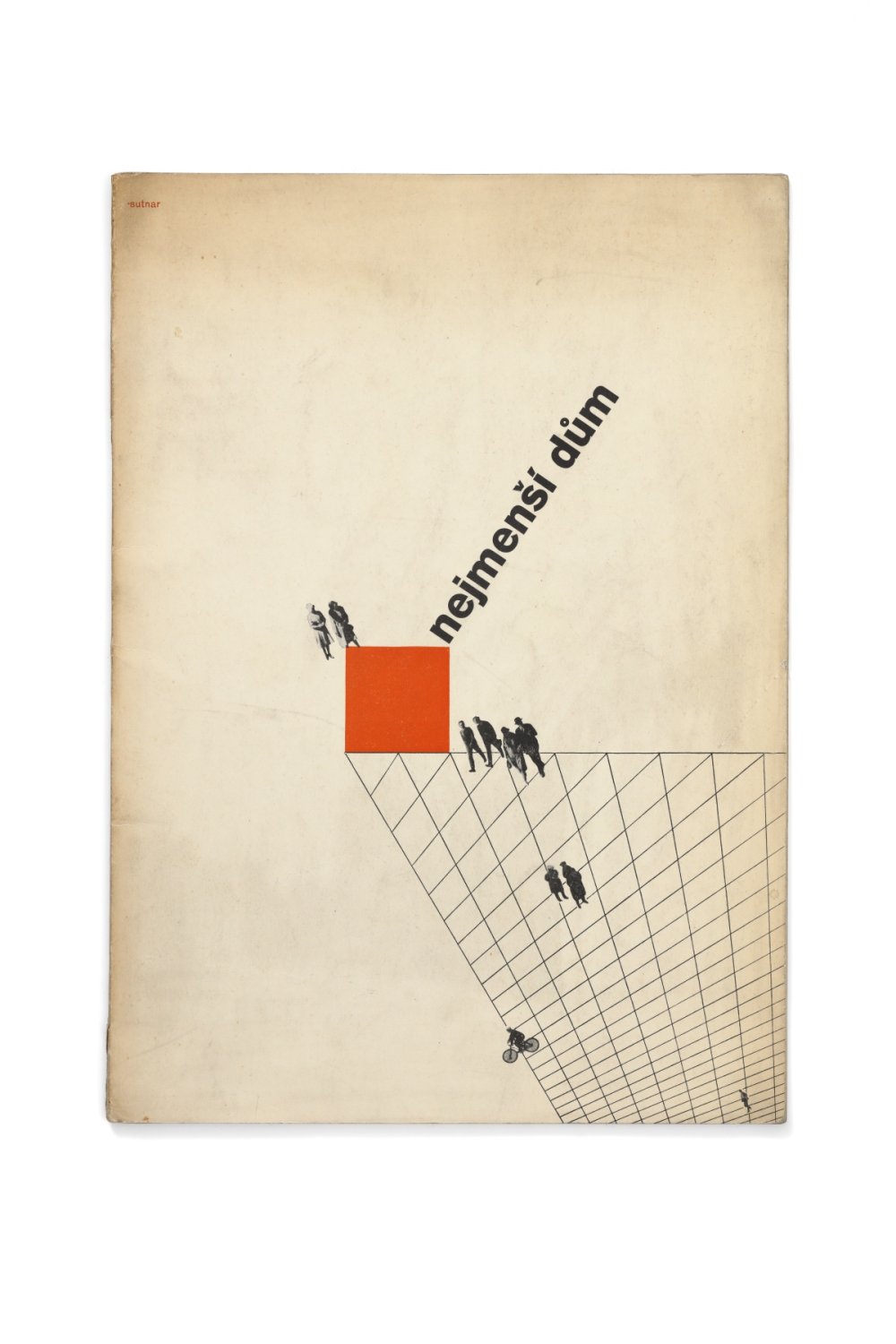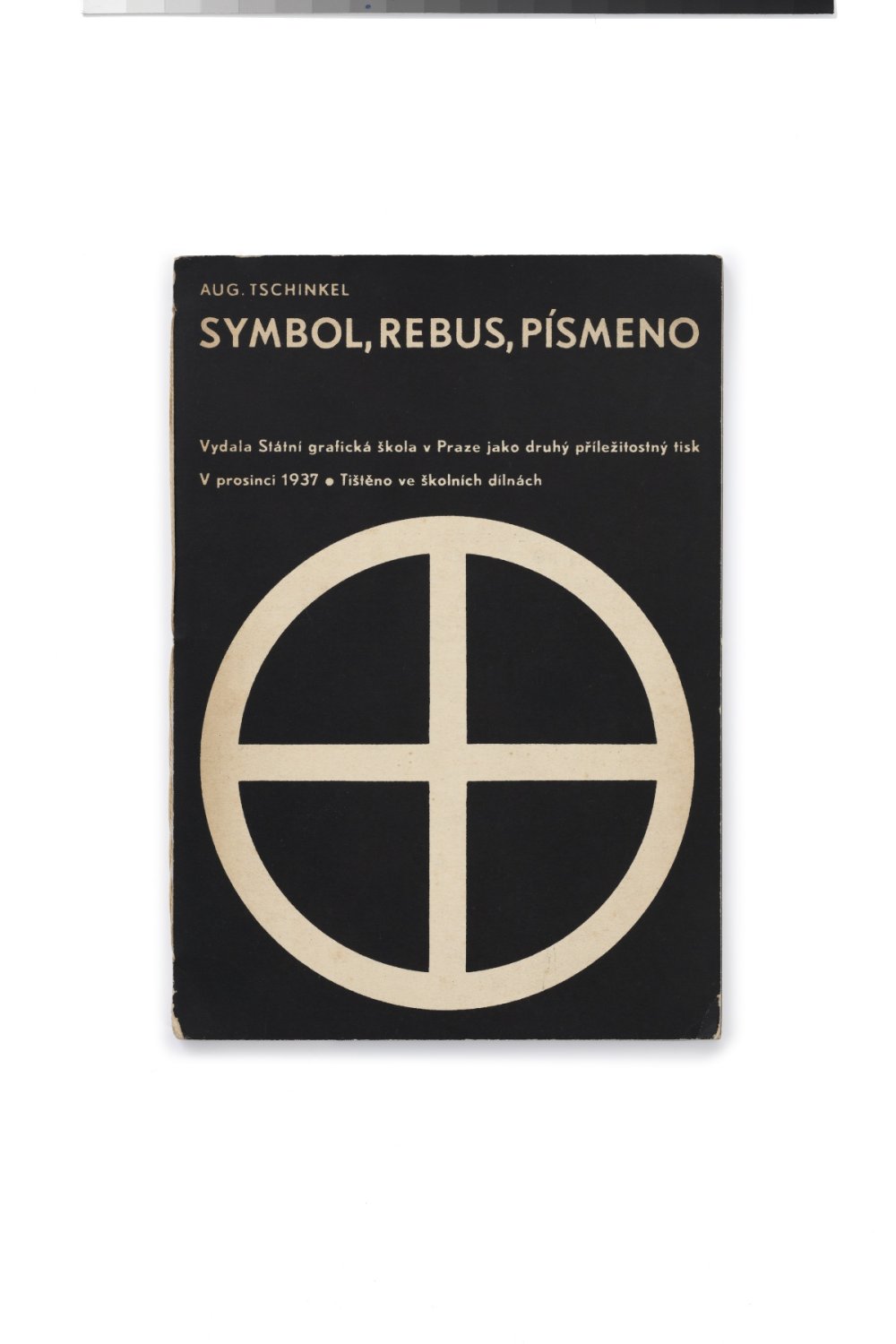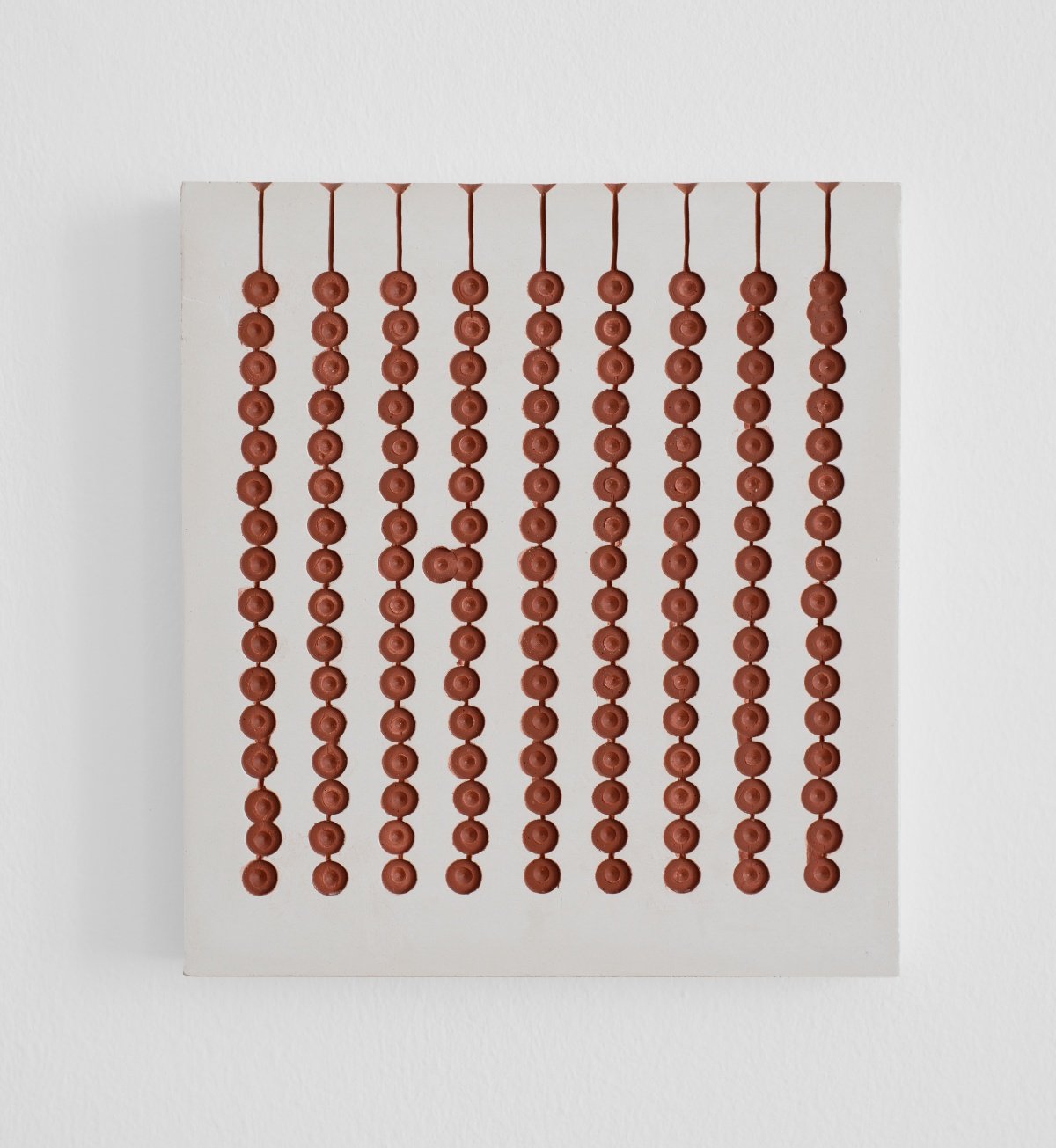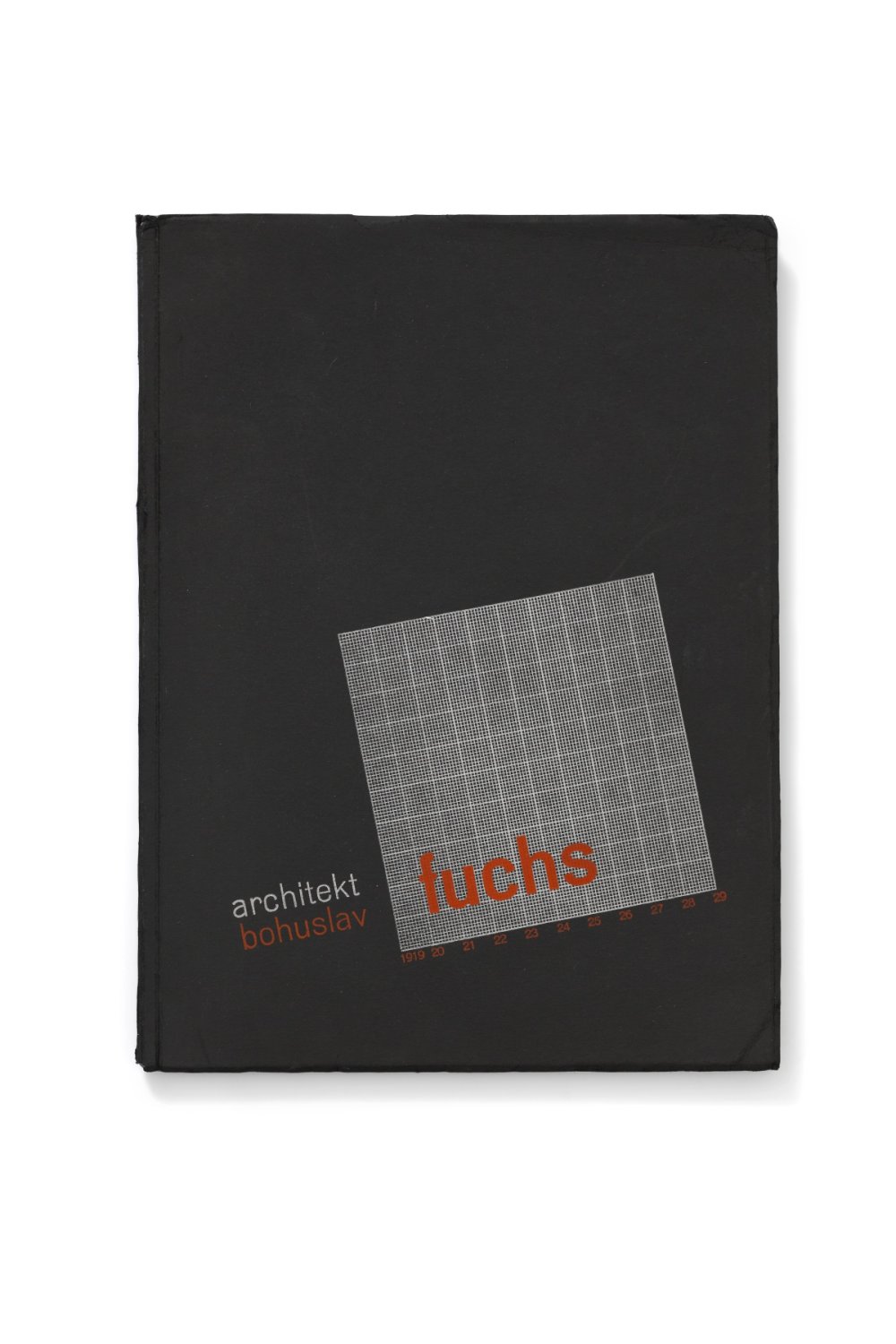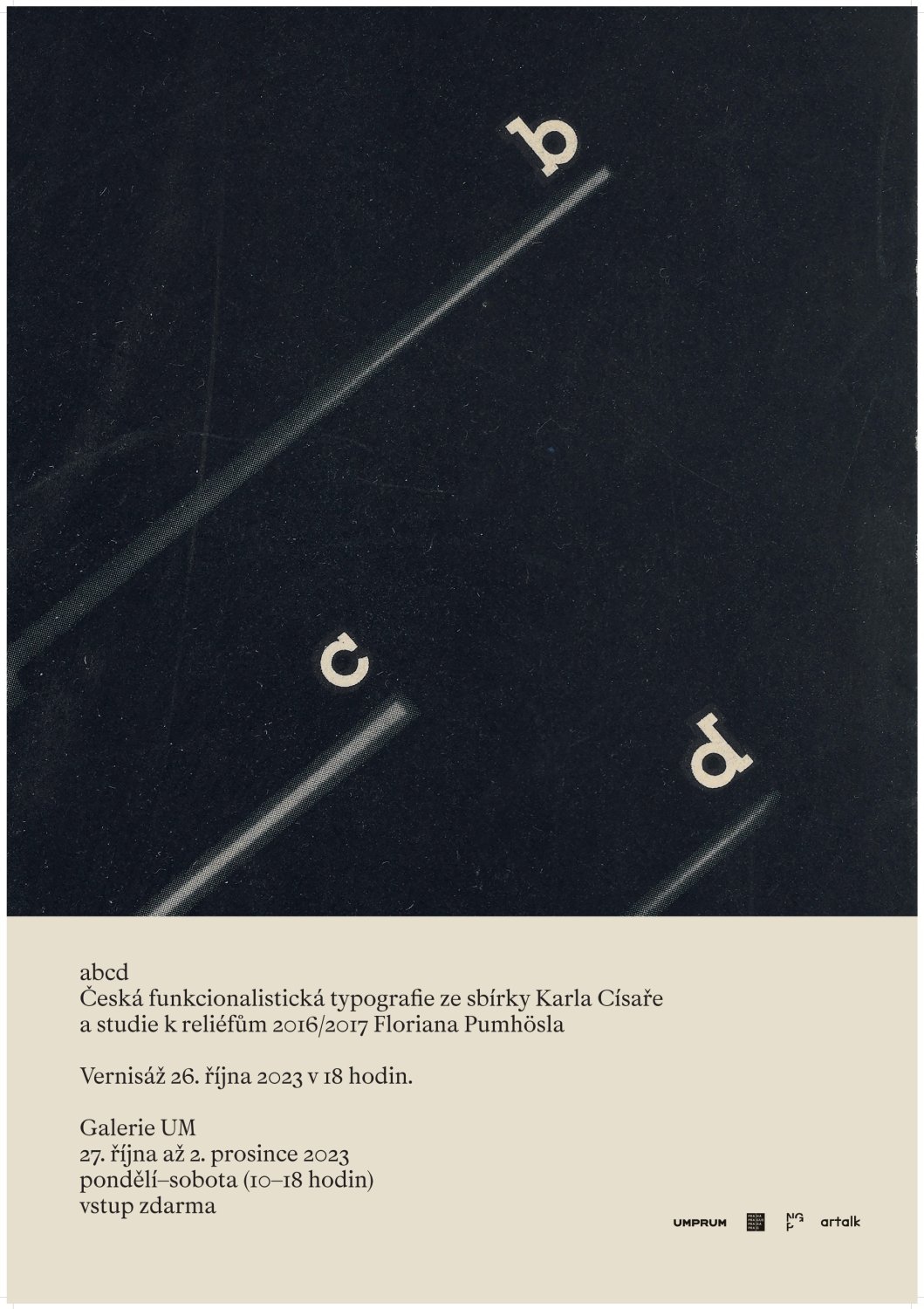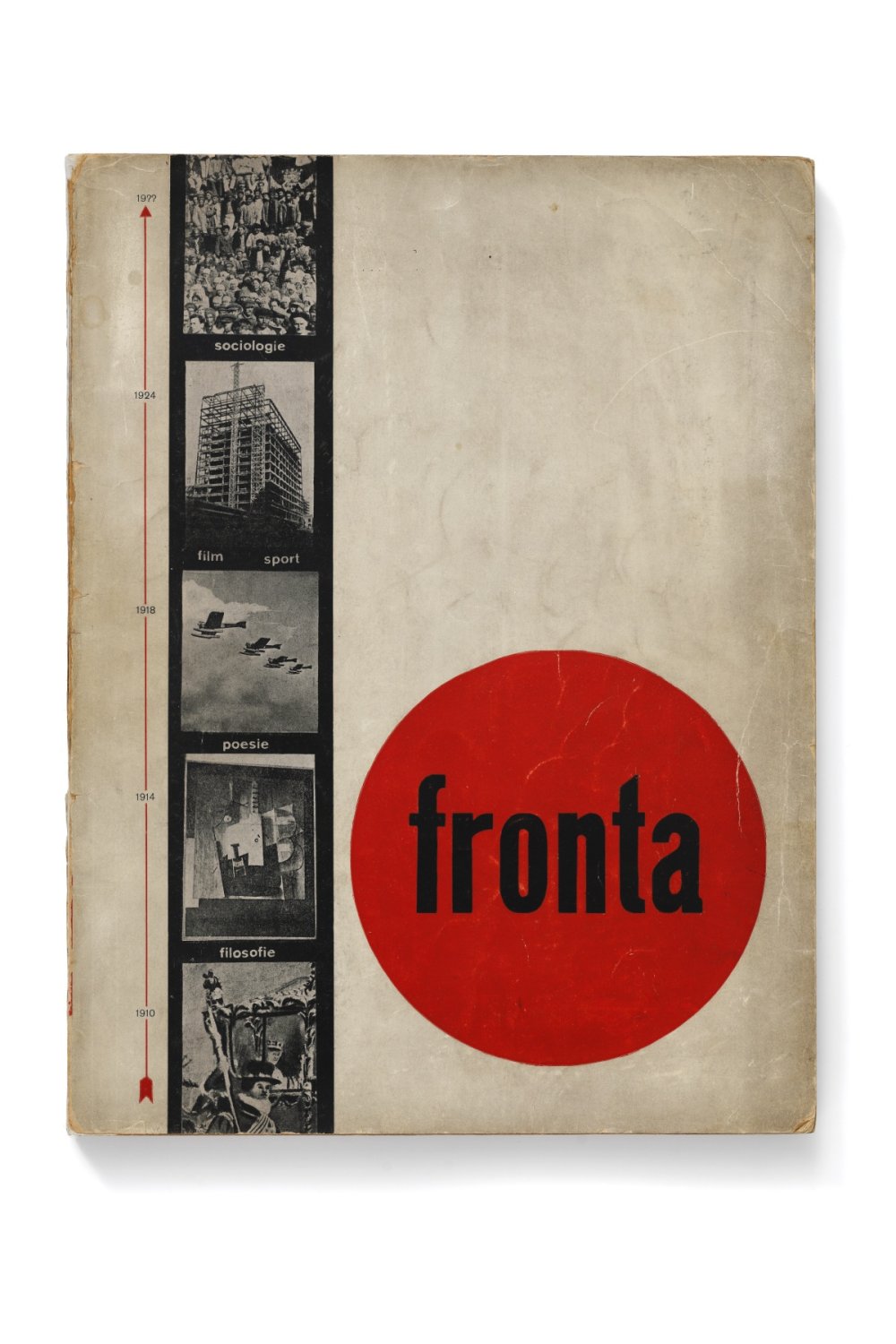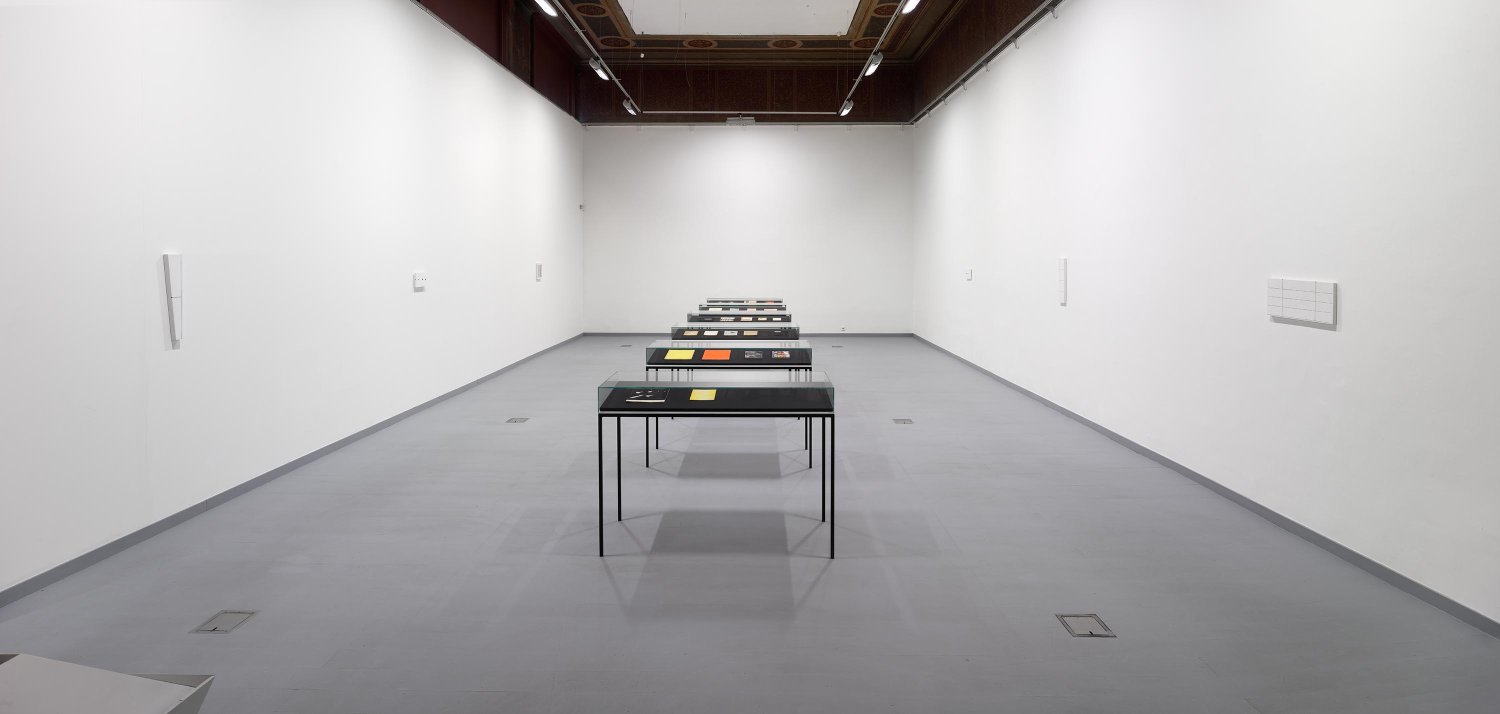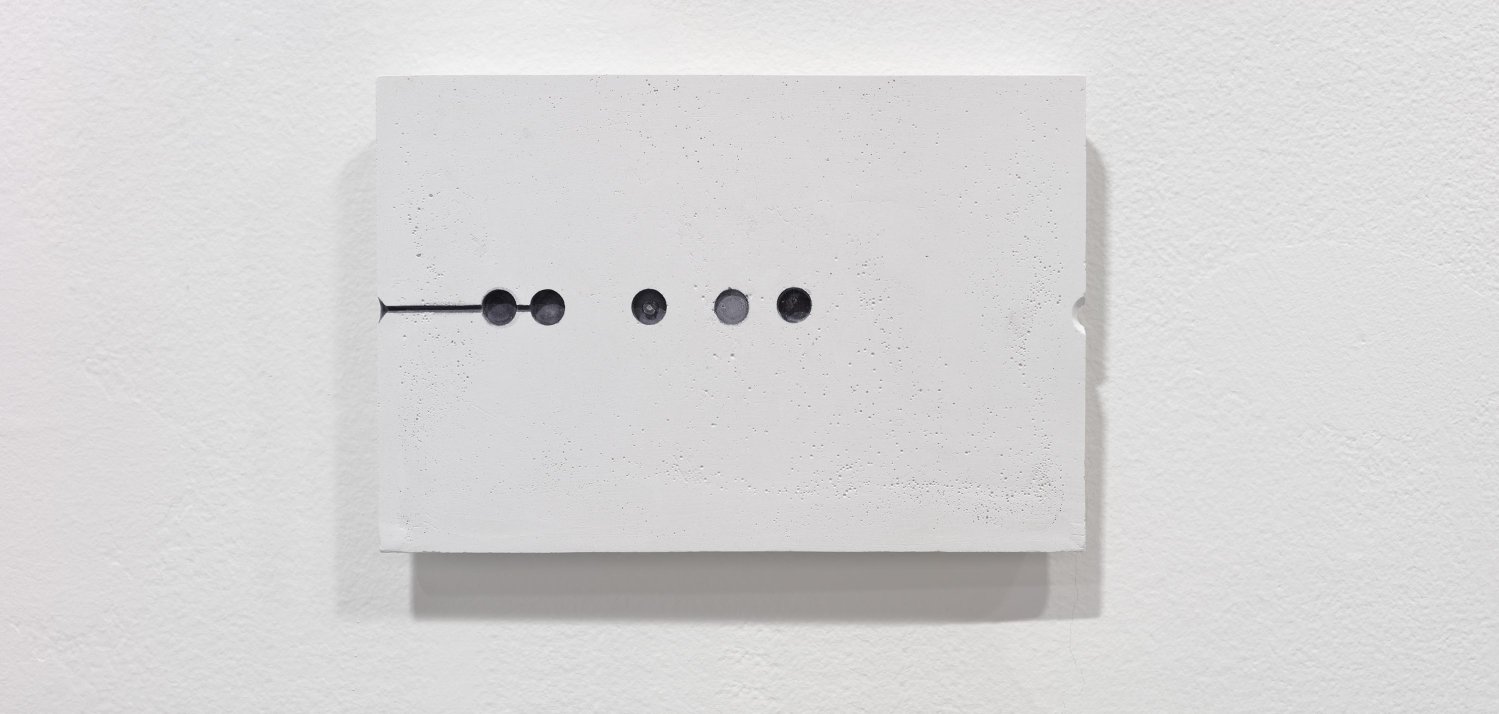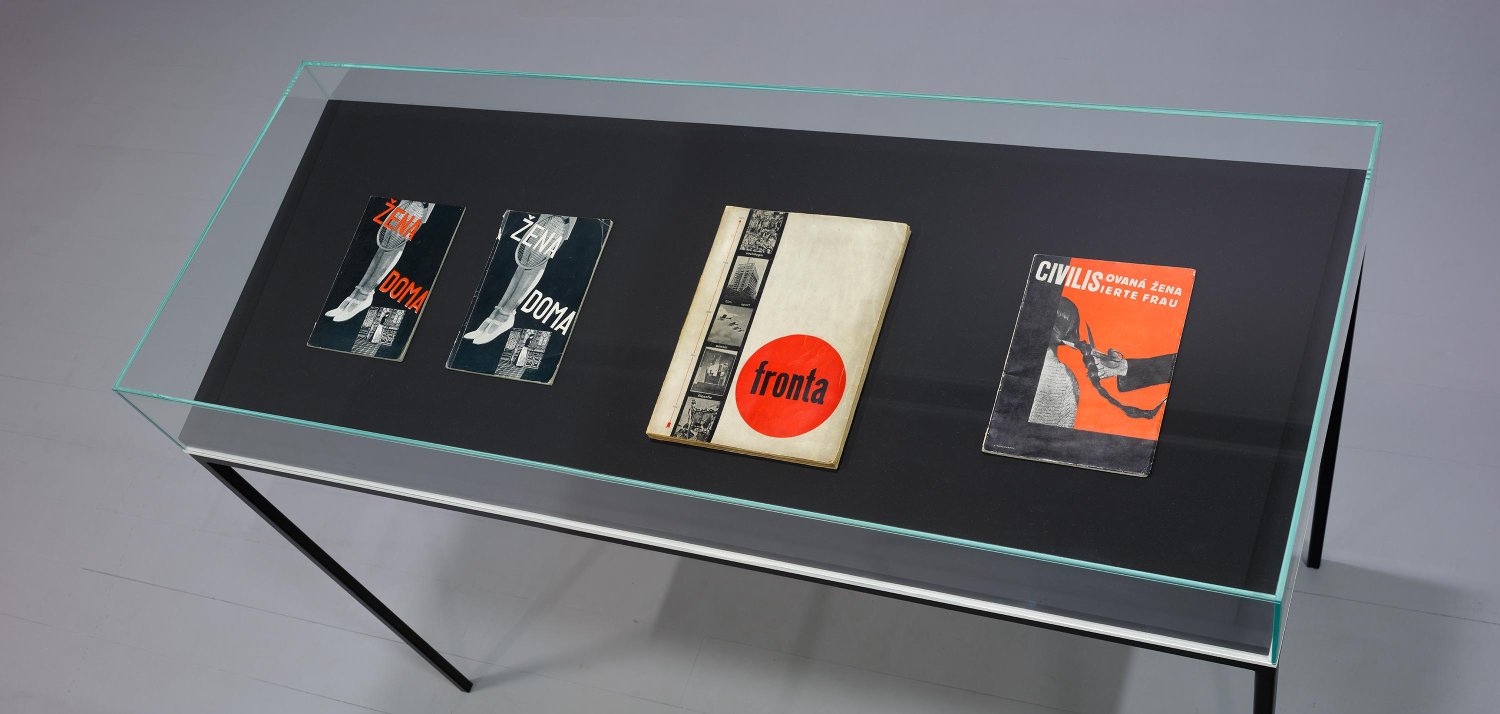
abcd - Česká funkcionalistická typografie ze sbírky Karla Císaře a studie k reliéfům 2016/2017 Floriana Pumhösla
abcd  - Česká funkcionalistická typografie ze sbírky Karla Císaře a studie k reliéfům 2016/2017 Floriana Pumhösla
„Sběratel se nejen přenáší do dalekého nebo minulého světa, nýbrž současně i světa lepšího, v němž sice lidé stejně jako v každodennosti nemají k dispozici to, co potřebují, v němž jsou však věci zbaveny oné roboty, která je nutí, aby byly užitečné.“
Walter Benjamin, Paříž, hlavní město devatenáctého století
V Galerii UM bude uvedena výstava abcd. Česká funkcionalistická typografie ze sbírky Karla Císaře a studie k reliéfům 2016/2017 Floriana Pumhösla, která vůbec poprvé zpřístupní nejvýznamnější ukázky ze sbírky funkcionalistické typografie filosofa, teoretika umění a pedagoga UMPRUM Karla Císaře. Nabídne takové poklady jako Rossmannův sborník Fronta, Teigovy architektonické publikace, Sutnarovy výstavní katalogy, Tschinkelovy didaktické příručky, nebo méně známé soukromé tisky Antonína Jera. V instalaci rakouského umělce Floriana Pumhösla zdůrazní především pro funkcionalismus charakteristické spojení abstraktních forem s fotografiemi nové věcnosti, které měly vést k vytvoření „nového druhu obrazového písma“.
„Výstava navazuje na skupinovou expozici „Obrazy a předobrazy“, kterou jsem před deseti lety připravil pro Galerii hlavního města Prahy v prostoru Městské knihovny. Zatímco ale tehdy jsem vztahoval díla čtyř současných zahraničních umělců ke středoevropskému meziválečnému výstavnictví, funkcionalistickému sklářství a surrealistické typografii, v Galerii UM nyní konfrontuji ukázky z vlastní sbírky české funkcionalistické typografie se studiemi k reliéfům 2016/2017 od rakouského umělce Floriana Pumhösla, jednoho z účastníků někdejší přehlídky“, shrnuje nejnovější expozici v Galerii UM její kurátor Karel Císař.
Většina funkcionalistických knižních obálek odpovídá charakteristice, jak ji publikoval Karel Teige v první stati o nové typografii „Moderní typo“ z roku 1927: rozcházejí se s tradicí, volí jednoduché a čitelné typy písma, vystihují specifický účel tiskoviny, vyvažují plochu podle optických zákonů, využívají nové technické objevy a jsou výsledkem spolupráce „projektanta-grafika“ s dalšími odborníky. Několik málo z těchto funkcionalistických obálek však zmíněnou charakteristiku porušuje: odvozují modernost od forem předmoderních, místo jednoduchého a čitelného písma používají dekorativní rukopisné písmo nebo napodobují časopiseckou tiráž, rezignují na vyváženou plochu a pokrývají ji fotografií vody, případně se drží archaického linorytu či jsou výsledkem práce pouze „projektanta-grafika“ v jedné osobě.
Florian Pumhösl vyšel z redukce funkcionalistické typografie v geometrii kreseb na skle, které byly součástí výstavy documenta 12 v Kasselu v roce 2007. V expozici společně s kresbami byly proto vystaveny i plexisklové boxy s ukázkami časopisu Front. Srovnáme-li jeho kresby z jejich grafickými zdroji, zjistíme, že neodkazují ani tak k textu či ilustraci, ale především k principům rozmístění optických jednotek na stránce. Zdvojená linie černých linek odkazuje k prázdnu, jež oddělovalo sekvenčně snímané záběry letu parašutistů ve zvláštním čísle časopisu Front z roku 1943. Podobně je tomu i v případě konstruktivistické obálky českého typografa Zdeňka Rossmanna, jejíž ukázku Pumhösl užil ve svém reliéfu z roku 2010: hladká plocha obálky představuje nejekonomičtější formu sdělení, kdy je naše pozornost vedena rychle a účelně.
Vzhledem k tomu, že Rossmann podobně jako další absolventi Bauhausu nebyl pouze typografem, ale i architektem a designerem výstav, zdánlivě abstraktní řešení jeho grafických prací vlastně představovalo diagram, který mohl být užit například i k choreografii pohybu návštěvníků v budově či na výstavě. A něco podobného platí i o Pumhöslových studiích k reliéfům 2016/2017. S funkcionalistickou typografií je totiž nespojují pouze disky a mřížky odkazující k podobným formálním elementům, jaké se nacházejí na knižních obálkách, ale především pochopení nepotištěných ploch grafických úprav a prázdných prostorů coby aktivních faktorů, které zabezpečují podobně rychlý a snadný pohyb fyzickým prostorem.
U příležitosti výstavy bude také vydána stejnojmenná publikace, ve které problematiku přiblíží jak bohatá fotodokumentace, tak podrobné komentáře. Záměrem není pouze prezentovat izolované knižní obálky, ale srovnat grafické řešení širších souborů a sledovat systematické užívání prázdného prostoru, redukované geometrické prvky, obrazové statistiky a fotomontážní postupy.
Architektonické zpracování výstavy: Florian Pumhösl
Fotografie: Markéta Slaná a Martin Polák
Karel Císař (nar. 1972, Praha) žije a pracuje v Praze. Vystudoval filozofii na Univerzitě Karlově (Ph.D., 2006) a na Ženevské univerzitě (Diplôme d'études supérieures, 2001). Od roku 2022 je profesorem teorie a dějin moderního a současného umění na Vysoké škole umělecko-průmyslové v Praze. Knižně vydal soubory esejů Abeceda věcí. Poznámky k modernímu a současnému umění (2014) a Signatury všech věcí. Poznámky k teorii moderního a současného umění (2021). Za první z nich byl nominován na Cenu F. X. Šaldy za vynikající výkon v oblasti umělecké kritiky za rok 2014. V témže roce byl oceněn pracovním grantem Ceny Igora Zabela za kulturu a teorii. Kurátorsky připravil například výstavy „Vzpomínky na budoucnost“ (Galerie Václava Špály, 2009), „Obrazy a předobrazy“ (Galerie hlavního města Prahy, 2013), „Sam Lewitt Cheyney Thompson. Síť. Gradient. Opilecký krok" (Dům umění města Brna, 2017) a „Lucy McKenzie & Atelier E.B“ (Galerie Meyer Kainer, Vídeň, 2022).
Florian Pumhösl (nar. 1971, Vídeň) žije a pracuje ve Vídni. V letech 1989-1997 absolvoval Höhere Grafische Bundes-Lehr- und Versuchsanstalt ve Vídni a v letech 1989-1996 studoval grafiku na Univerzitě (tehdy Vysoké škole) užitého umění ve Vídni. Od roku 2018 je profesorem sochařství na Akademii výtvarných umění v Mnichově. Pumhösl se zúčastnil mnoha mezinárodních skupinových výstav, mimo jiné 50. Benátského bienále (2003), 27. Bienále v São Paulu (2006) a Documenta 12 v Kasselu, Německo (2007). Samostatně vystavoval mimo jiné ve Wiener Secession, Vídeň (2000), v Kölnischer Kunstverein, Kolín nad Rýnem, Německo (2003) MUDAMu, Lucemburk (2009), v Kunstverein für die Rheinlande und Westfalen, Düsseldorf (2010), v MUMOKu, Vídeň (2011), v Raven Row, Londýn (s Mathiasem Polednou 2011), Kunsthaus Bregenz (2012/2013), v Haubrok Foundation, Berlín (2015), Nejnověji Pumhösl vystavoval společně Vincentem Fecteau v MAK Center Schindler House v západním Hollywoodu na přelomu let 2021/2022.
Nejmenší dům. 18 projektů ze soutěže Svazu československého díla na typ nejmenšího řadového a volného rodinného domu, sestavili Oldřich Starý a Ladislav Sutnar, upravil Ladislav Sutnar, Praha, Svaz československého díla v Praze, t. Prometheus Praha (květe
Tschinkel, Augustin, Symbol, rebus, písmeno, Praha, Státní grafická škola v Praze, tištěno ve školních dílnách, Praha (prosinec) 1937, 21 × 14,6 cm. Příležitostný tisk. Sv. 2.